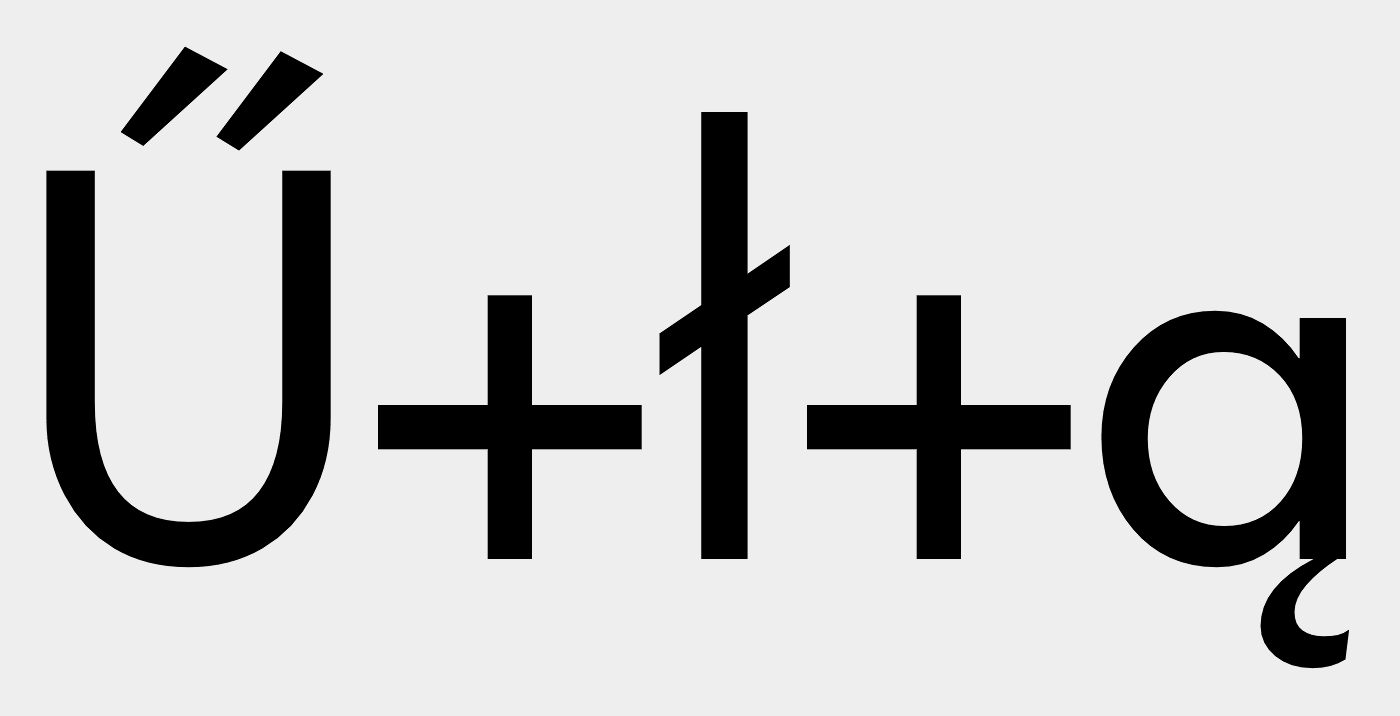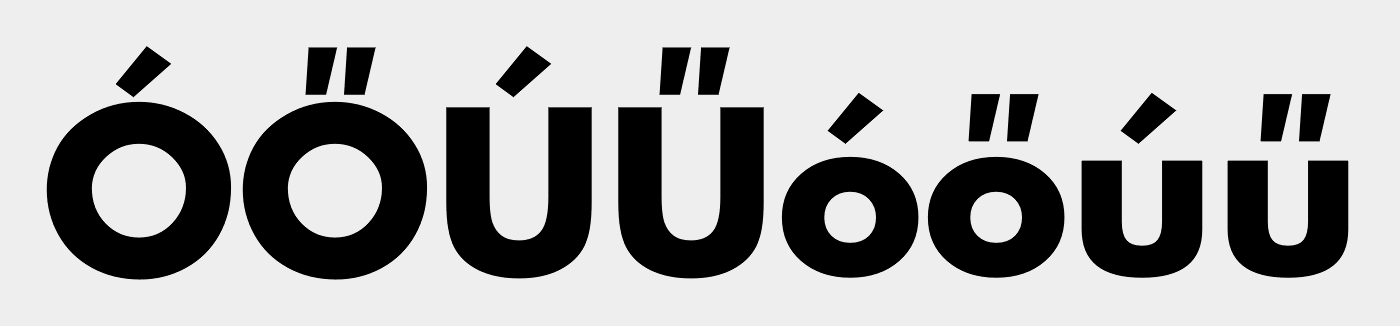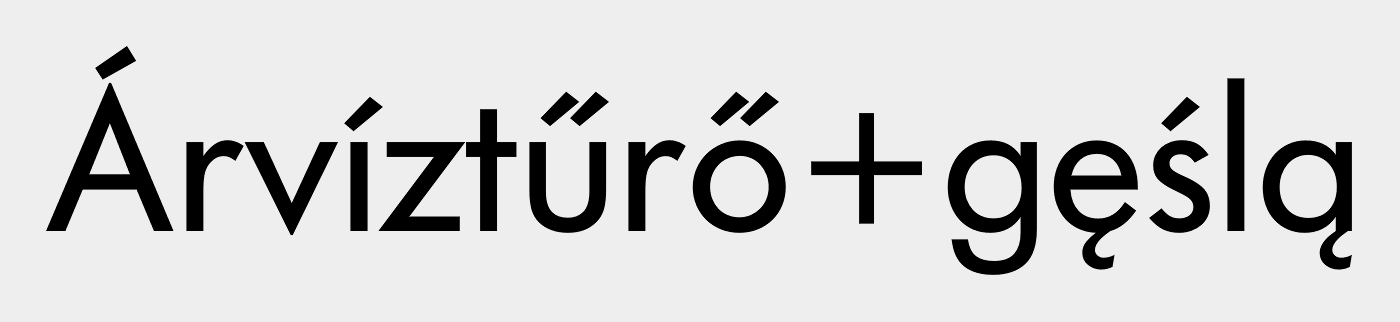
Futura T - OpenType-Schrift - Alternative
kurz vorweg - ich befasse mich beruflich erst seit Kurzem mit Typo. Deshalb verzeiht schon mal im voraus etwaige dumme Fragen. Aber ich brauche dringend einen Tipp.
Ich bin auf der Suche nach einer alternativen Schriftart für die Futura T - am liebsten OpenType.
Grund: Ich muss unterschiedliche Übersetzungen in ein bereits bestehendes Layout laufen lassen und steh jetzt vor dem Problem, dass Futura T leider nicht die passenden Glyphen des Polnischen und Ungarischen hat.
Kann mir hier jemand einen Tipp geben?
Von der Linotype-Version würde ich für ungarische Anwendungen die Finger lassen, zumindest wenn nicht klar ist, welche Schnitte evtl. je benötigt werden. In einigen Schnitten passen die Akuts und Doppelakuts nämlich nicht überhaupt nicht zueinander; das schließt einen vernünftigen Einsatz im Ungarischen praktisch aus.
Ein paar Beispiele folgen. Im ersten geht’s, im zweiten nicht. Bei den leichten Schnitten ist es genau so.